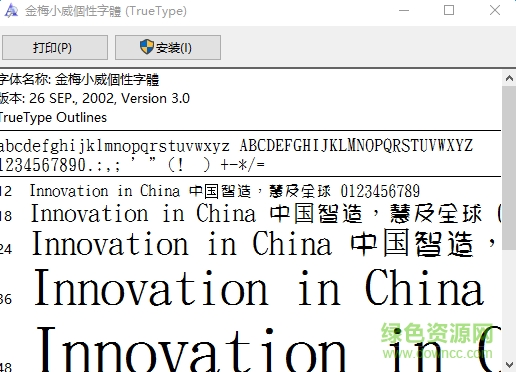
金梅小威個性字體是金梅字庫中比較有特色的一款字體,就像它的名字一樣是很有個性的,可以用于很多方面,書本印刷、影視設(shè)計、廣告設(shè)計等都可以,歡迎有需要的朋友來綠色資源網(wǎng)下載。
金梅小威個性體是一款比較不一樣的字體,它不像有些字體那樣呆板,它是很有活力的,而且很好看,屬于那種很耐看的字體,大家肯定也會喜歡這款字體的。